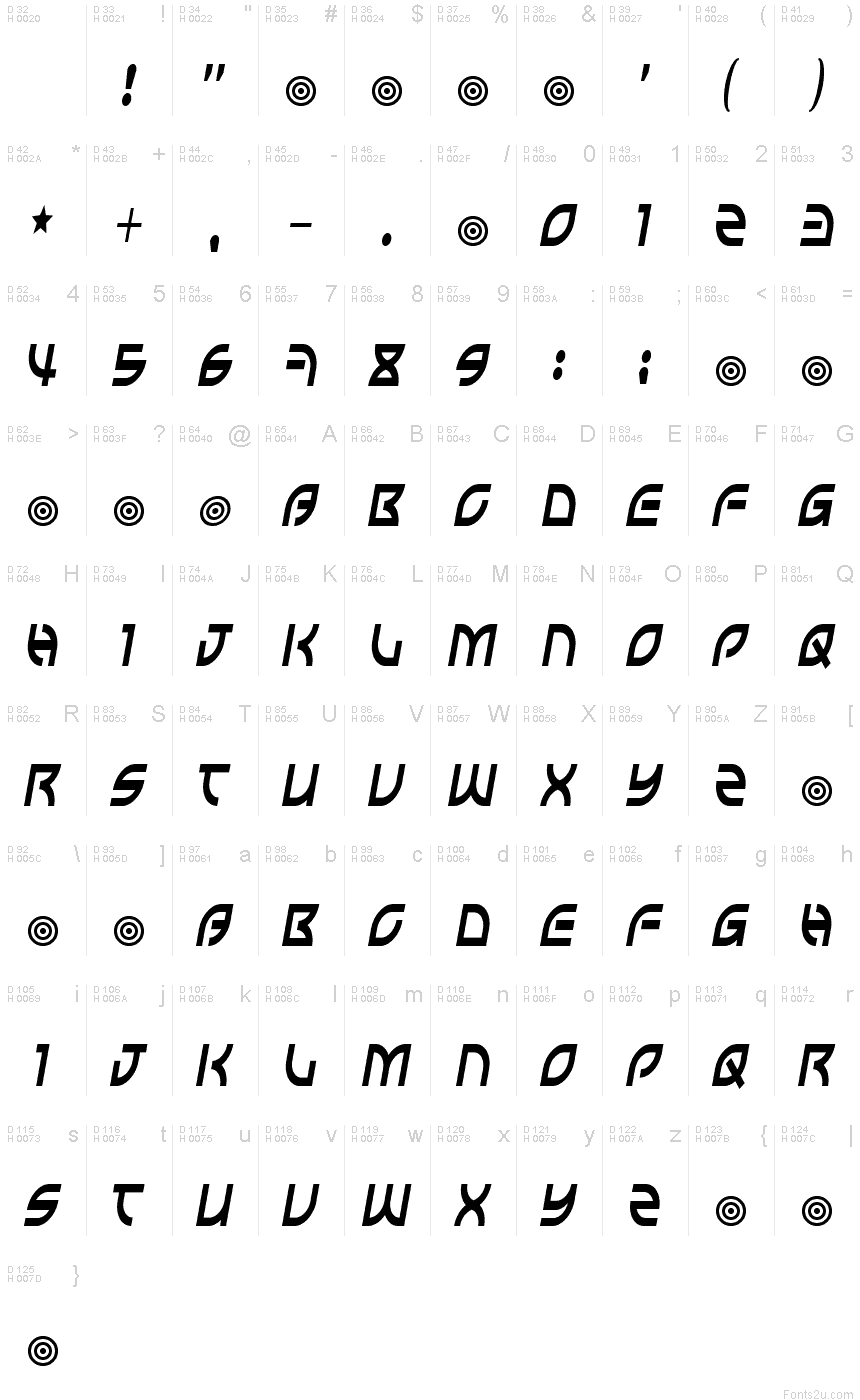
Wisecrack autorstwa Jakoba Fischera to darmowy, futurystyczny krój typu display o szybkim, poszatkowanym rytmie i eleganckim stylu retro-tech. Litery opierają się na ostrych przekątnych, głębokich wycięciach i zaokrąglonych zewnętrznych łukach, dzięki czemu krój sprawia wrażenie opływowego i mechanicznego, nie będąc przy tym chłodnym w odbiorze.
Świetnie sprawdza się na plakatach sci-fi, w logotypach gier, na okładkach płyt, ekranach powitalnych aplikacji czy planszach tytułowych, gdzie krótkie słowa potrzebują ruchu, a nie ozdobników. Jako darmowy font, doskonale nadaje się też do wyrazistych nagłówków lub kompaktowego brandingu, ponieważ wycięte łączenia i zamaszyste krzywe sprawiają, że nawet kilka liter nabiera energii i kierunkowości.
Wisecrack